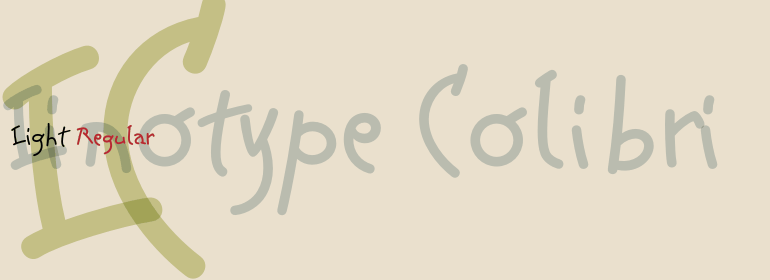
Linotype Colibri™
Linotype Colibri™,这款字体结构工整、笔画清晰,兼顾美观与易读性,适用于标题、正文、海报、包装、LOGO 等多种场景。字形优雅稳定,风格百搭耐看,适配日常排版与创意设计,让文字呈现更舒适、更具质感。Linotype Colibri™一笔一画,皆是细节,以均衡的比例、流畅的线条打造舒适视觉体验,字形端正大气,风格简约现代。无论是商业设计、品牌宣传还是日常排版,都能轻松驾驭,让文字更有格调与力量。Linotype Colibri™字体下载。
字体品牌: Linotype(Monotype) 设计师:Ellenberger,Hans-Jürgen 字体分类:手写风格字体 字体属性:外文 字符集:Unicode 发布时间: 2018